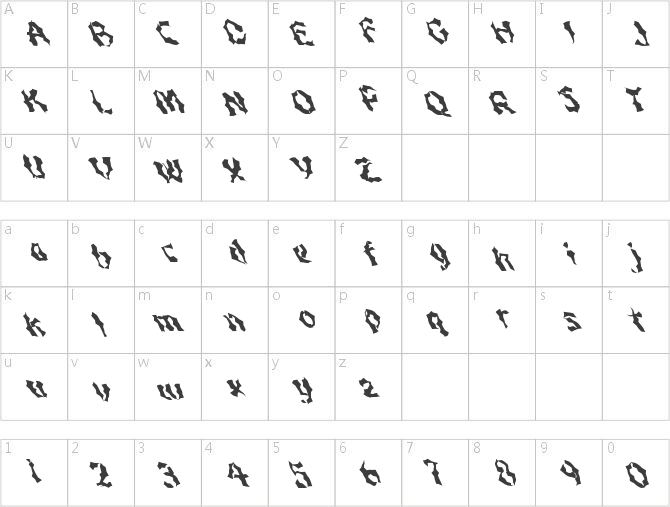
FZ WACKY 49 LEFTY 詳情頁(yè)
FZ WACKY 49 LEFTY字體字庫(kù)是一款讓人賞心悅目、百看不厭的英文字體,適合各類(lèi)廣告和產(chǎn)品包裝設(shè)計(jì)應(yīng)用,字體大小0.06MB,格式為ttf字體,上傳用戶是……西央,作者/版權(quán)方為未知